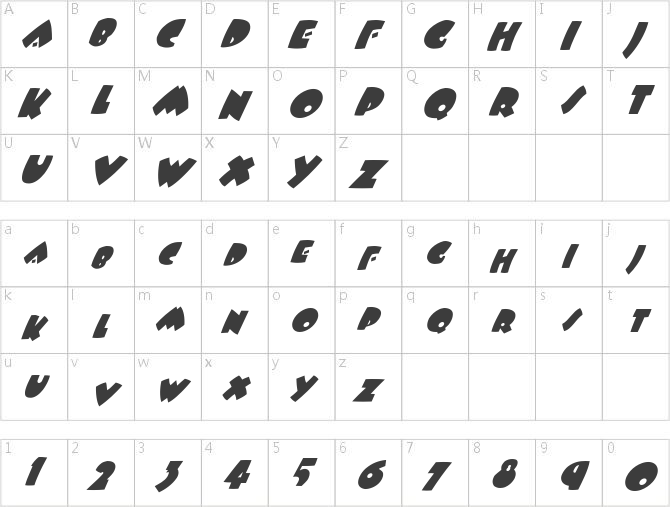
FZ JAZZY 9 ITALIC
FZ JAZZY 9 ITALIC介紹
FZ JAZZY 9 ITALIC字體字庫是一款讓人賞心悅目、百看不厭的英文字體,適合各類廣告和產品包裝設計應用,字體大小0.04MB,格式為ttf字體,上傳用戶是那是不變的,作者/版權方為未知
FZ JAZZY 9 ITALIC效果圖